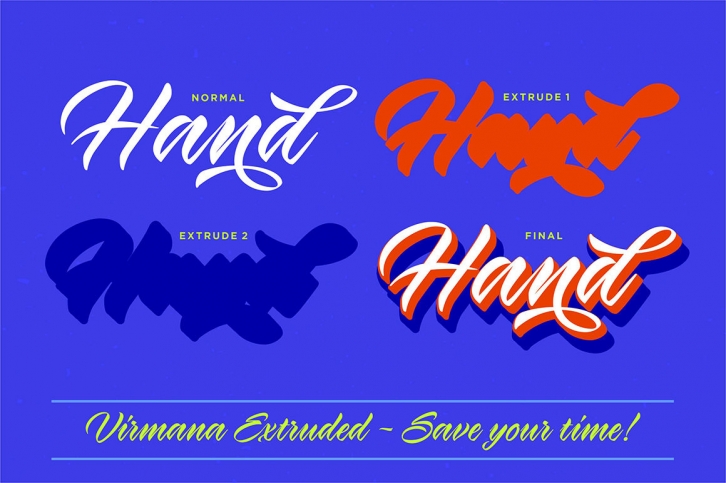
Ucapkan salam kepada Virmana Script Kuas naskah kaligrafi, elegan, menyenangkan, dan main-main dengan razia. Fitur Fitur terbuka, alternatif gaya, ligatur dan Berbagai Internasional untuk sebagian besar Bahasa Barat. Anda mendukung program yang mendukung fitur OpenType seperti Adobe Illustrator CS, Adobe Photoshop CC, Adobe Indesign.
Sempurna untuk membuat desain modern seperti logo, pencitraan merek, poster, media sosial, undangan pernikahan, judul, desain pakaian, dan banyak lagi. Semua huruf kecil termasuk alternatif gaya, awal & akhir, yang membuat font terlihat luar biasa!